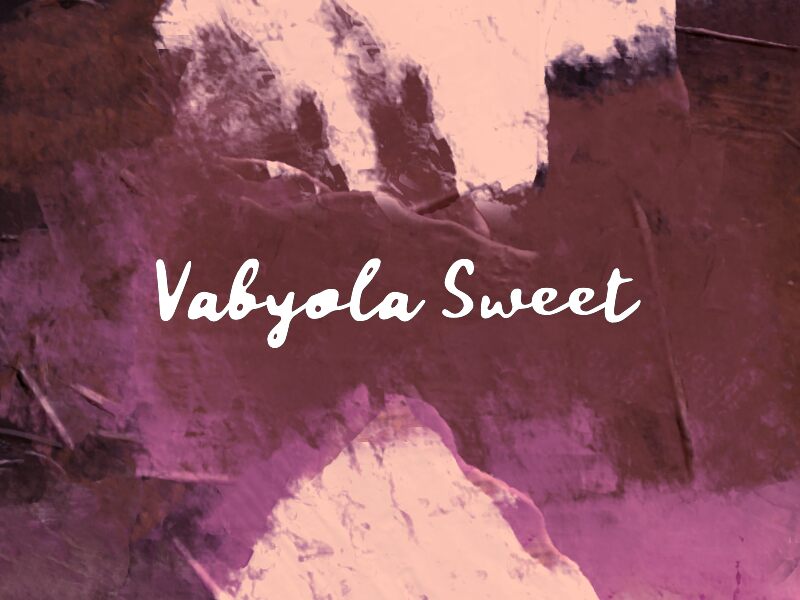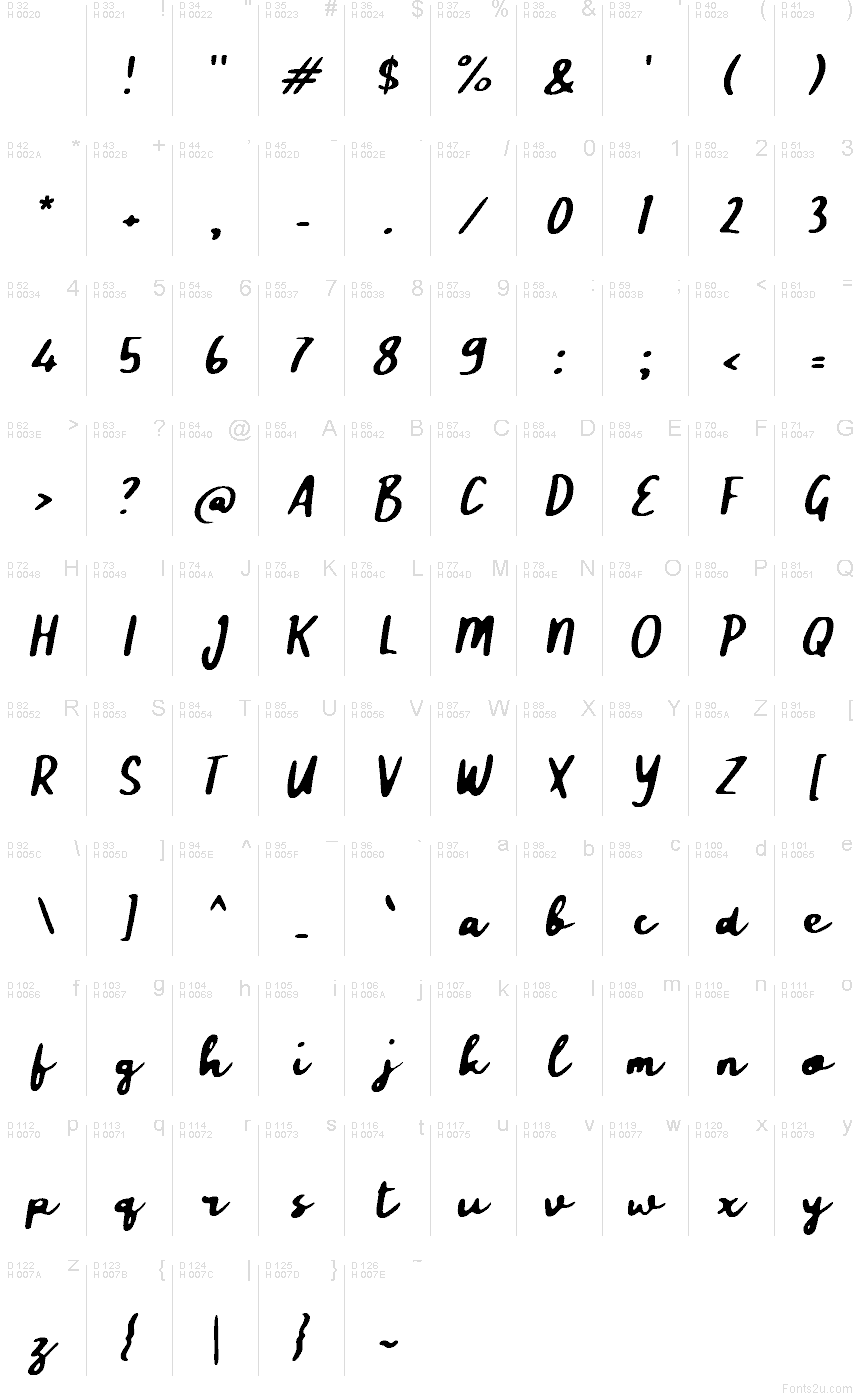
Vabyola Sweet
Vabyola Sweet de Ikiik es una tipografía manuscrita gratuita definida por un ritmo de pincel fluido y trazos redondeados que dotan a las letras de un movimiento natural. Sus uniones en bucle y formas cerradas, similares a gotas, le confieren una cadencia suave; gracias a esto, el estilo se siente desenfadado y orgánico, en lugar de rígido o excesivamente caligráfico.
Este movimiento marcado del pincel funciona de maravilla en logotipos de cafeterías, packaging, publicaciones en redes sociales, titulares de invitaciones y diseños de pegatinas donde prima la calidez sobre la formalidad. Las frases cortas aprovechan especialmente estas conexiones fluidas, que logran darle peso a un título o una firma sin perder esa frescura necesaria.